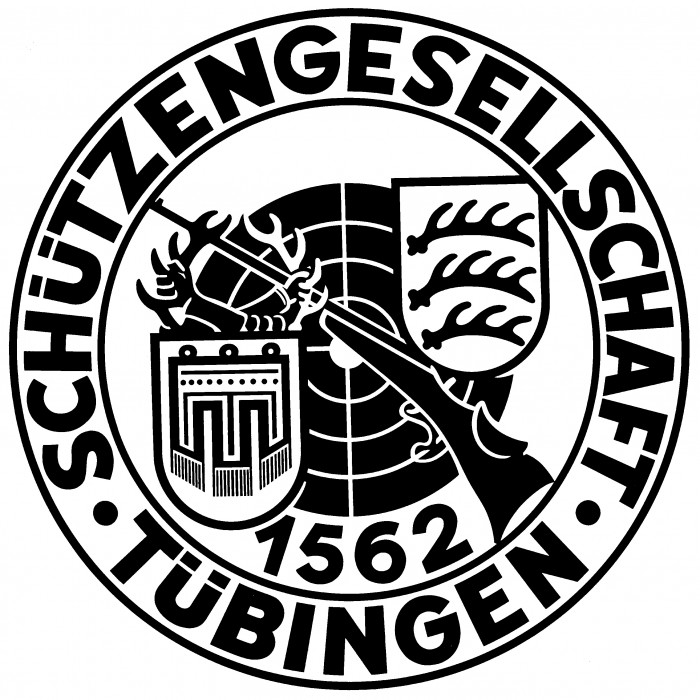
Schriftart aus Vereinswappen gesucht
Ich bin auf der Suche nach der Schriftart (oder einer ähnlichen) aus einem Vereinswappen. Welche Schriftart könnte das gewesen sein bzw. sieht so ähnlich aus?
So leicht etwas wackelig, wie die Buchstaben aussehen, hat der Grafiker, der das ganze Logo gezeichnet hat auch duie Schrift frei mit der Hand gezeichnet. Ich glaube kaum, dass er oder siwe hierzu eine bestimnmte, benannte Schriftart zur CVorlage hatte, noch dass diese hierzu überhaupt benötigt wurde.
wie schon angedeutet ist diese Schrift sicherlich handgemalt. Den Buchstaben und Ziffern nach könnte eine Fette Erbar Grotesk (http://de.wikipedia.org/wiki/Jakob_Erbar, 1926) die Vorlage geliefert haben. Bis auf die beiden S und s passt das recht gut:
Die beiden S und s gehen IMHO eher nach der Futura ( Paul Renner, 1927):
Auch noch eine Schrift in dem Stil ist die Neuzeit Grotesk (Wilhelm Pischner, 1928), erst mal zum Ansehen und die Schrift von der Zeit her besser einordnen zu können:
Es handelt sich also um eine typische deutsche geometrische Grotesk aus der zweiten Hälfte der 1920er. Als normale Fließtextschrift für das Logo könntest Du IMHO die Erbar Grotesk oder die Neuzeit Grotesk heranziehen. Die Neuzeit Grotesk findest Du in der Bitstream-Schriftensammlung die mit den Corel-Produkten (zB Corel Draw) mitgeliefert wurde als Geometric 706 bezeichnet. Mit der Neuzeit Grotesk Black als Vorlage könntest Du u.U. das Logo auch nachbauen.